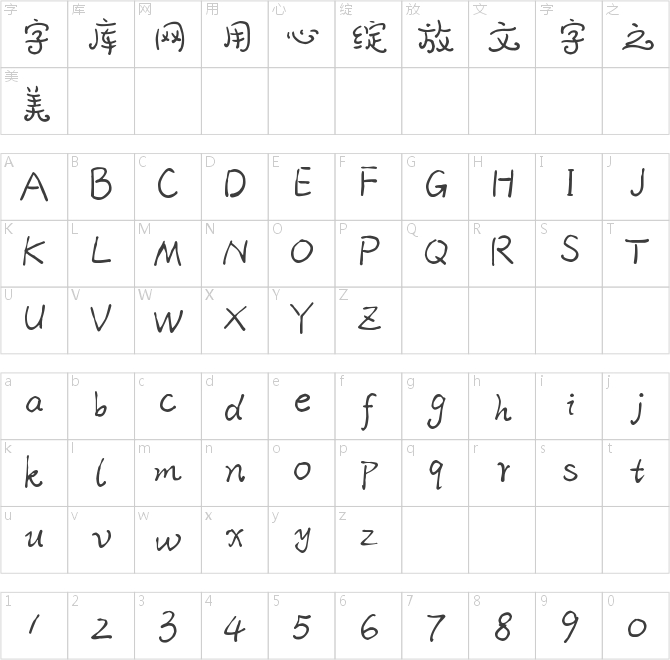
華鈦傲嬌公舉W5 詳情頁
字體名稱: 華鈦傲嬌公舉W
華鈦傲嬌公舉W5
華鈦傲嬌公舉W5介紹
華鈦傲嬌公舉W5字體字庫是一款讓人賞心悅目、百看不厭的中文字體,適合各類廣告和產品包裝設計應用,字體大小3.32MB,格式為ttf字體,上傳用戶是13226568769,作者/版權方為華鈦
華鈦傲嬌公舉W5效果圖